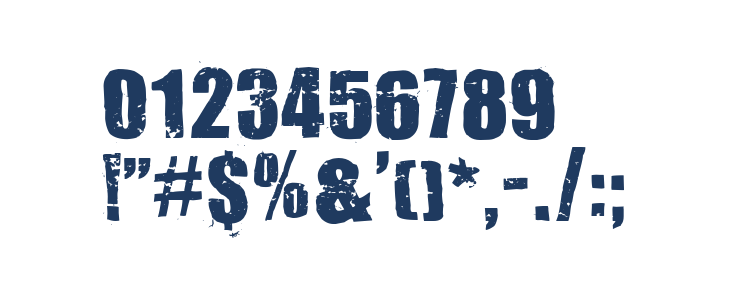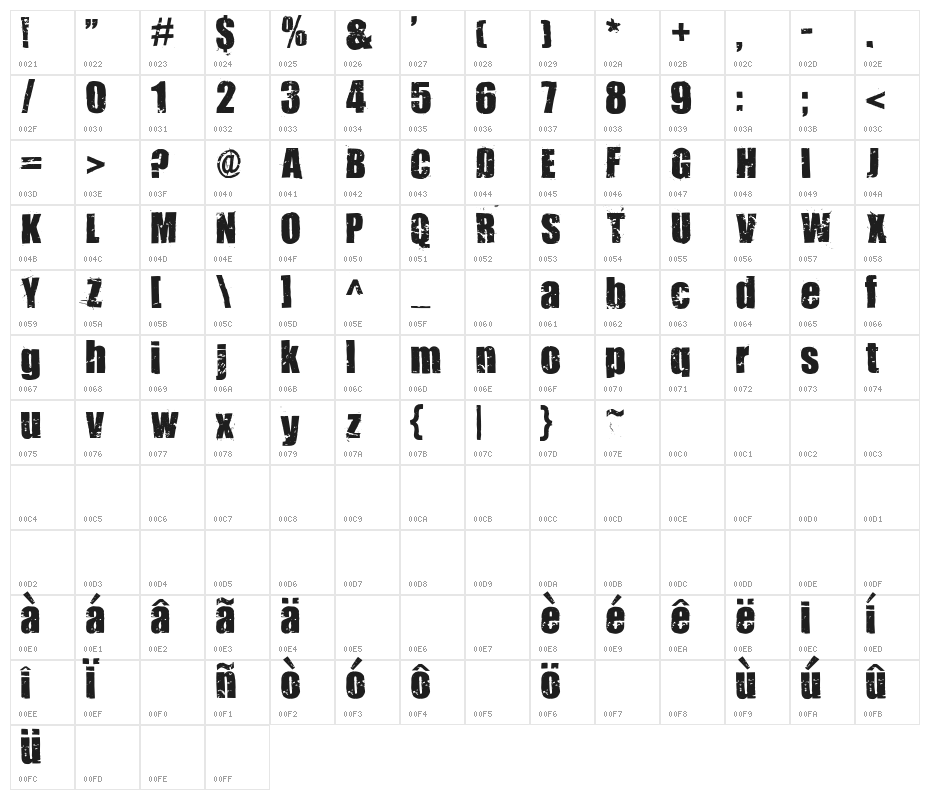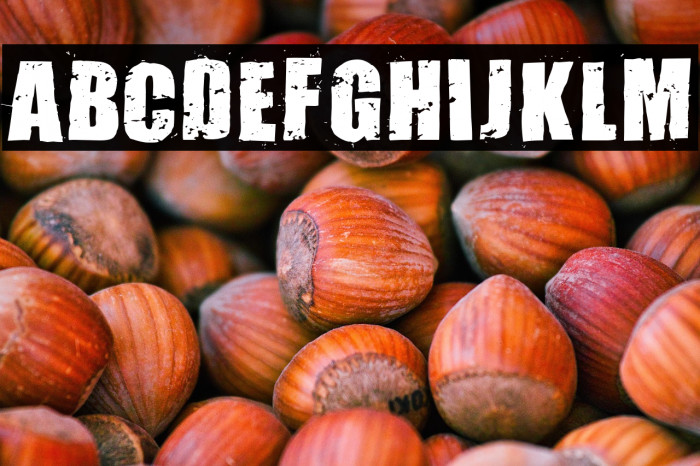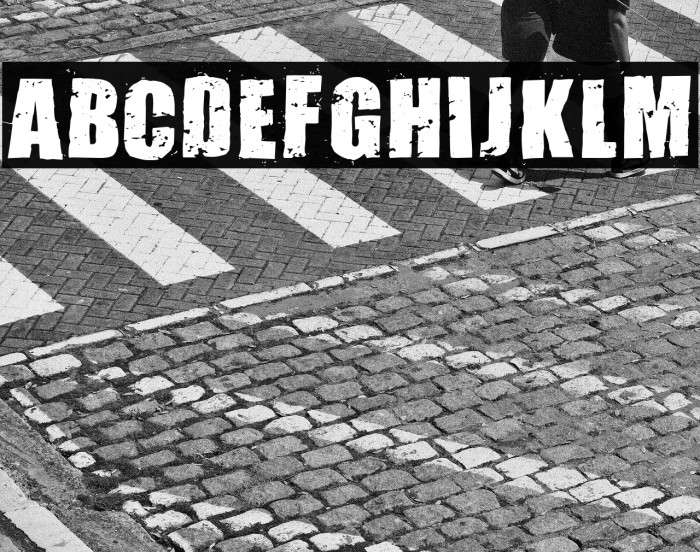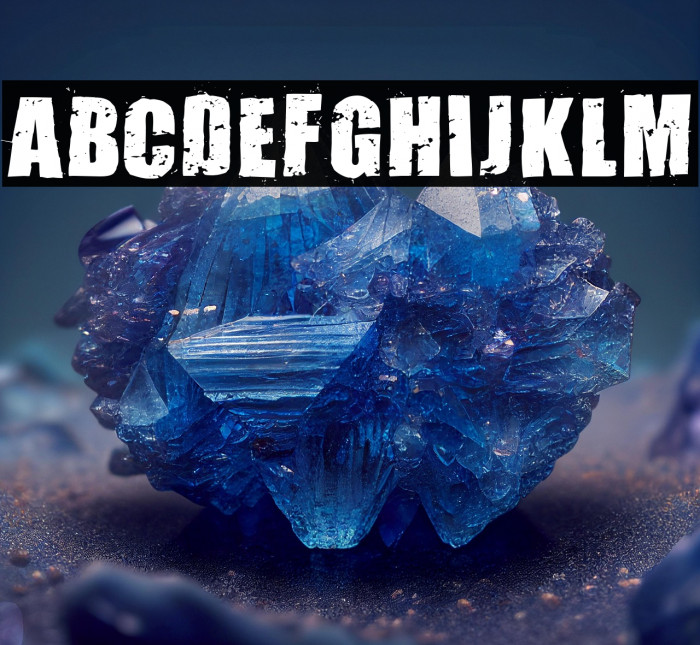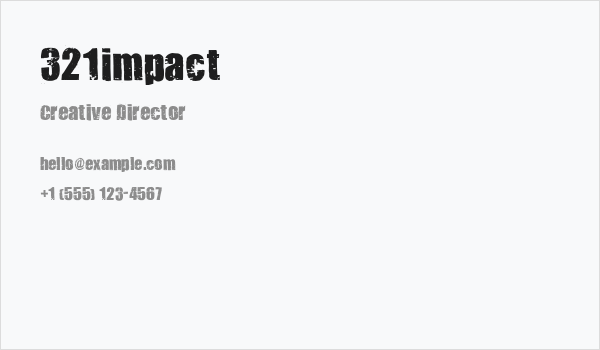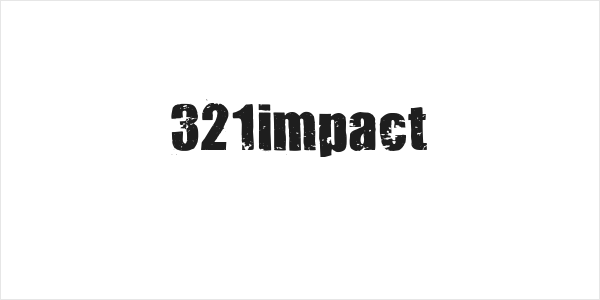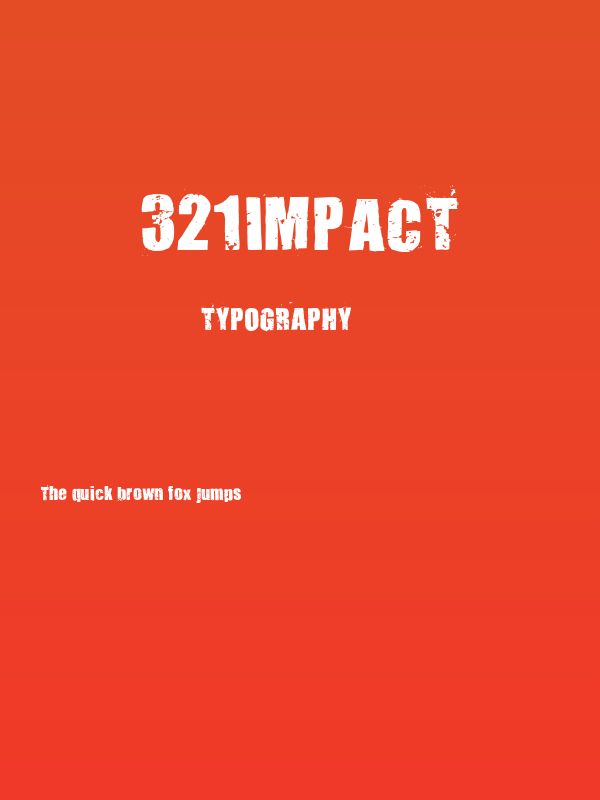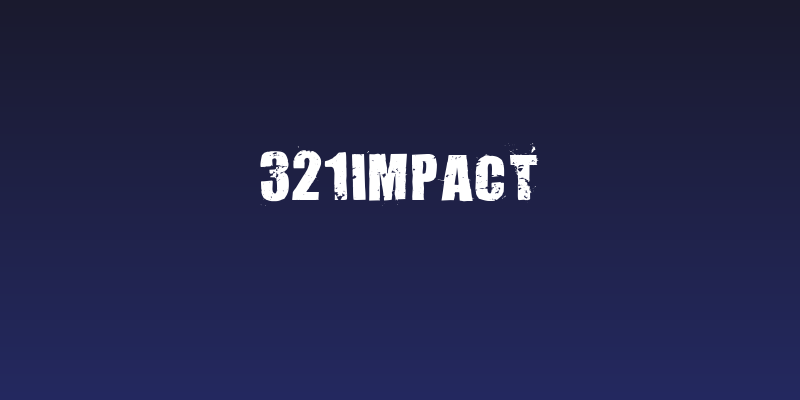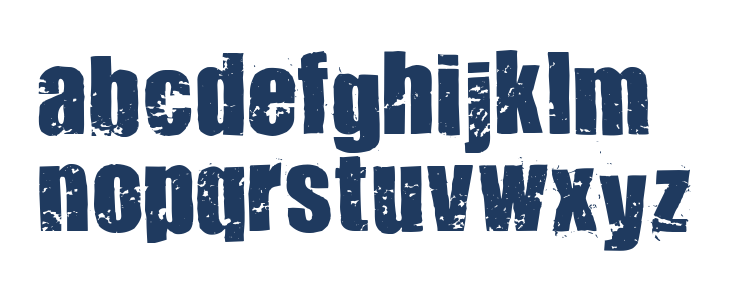
321impact Font
✎ Messy
| Gesamtstil | Vintage, Industrial |
| Vorgeschlagene Projekte | Ideal for posters, album covers, branding for edgy products, or any design needing a strong, vintage-industrial feel. |